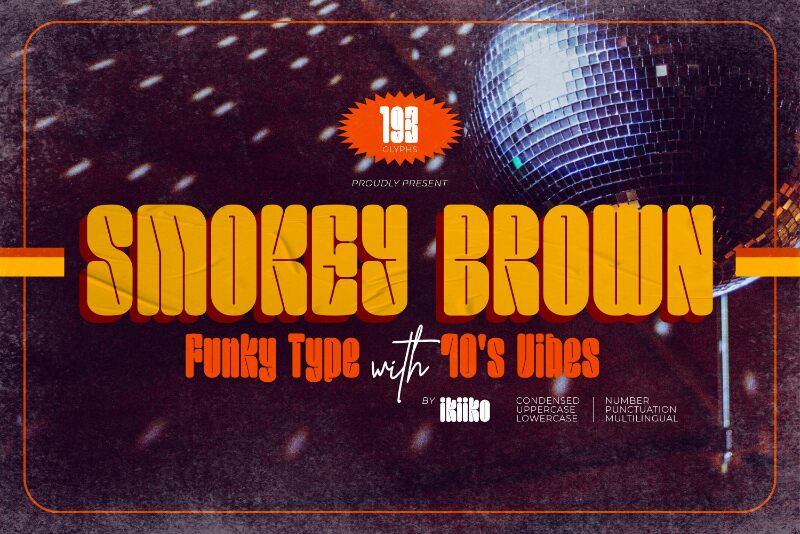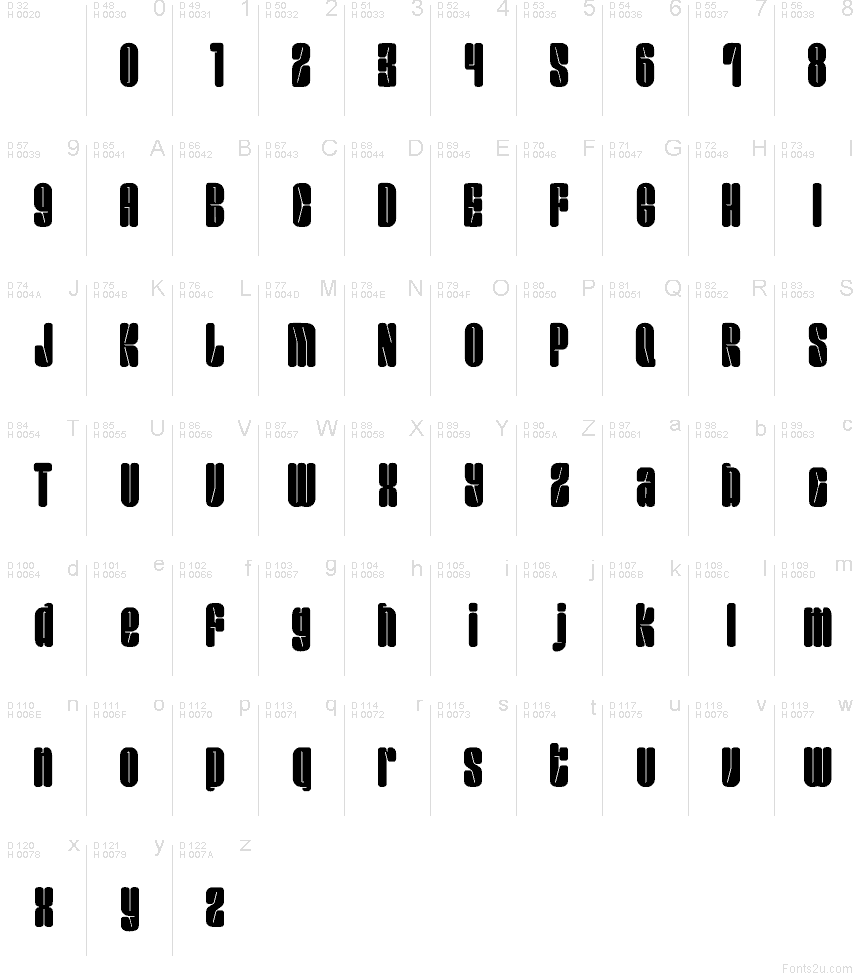
Smokey Brown od Ikiiko Type je bezplatné groovy bezpatkové písmo, které stojí na plných, vzpřímených tvarech. Působí hutně a kompaktně, s typickými úzkými drážkami uvnitř písmen. Tato silueta dodává písmu výrazný vzhled plakátů ze 70. let, kde zaoblené hrany udržují měkkost, i když je celková černá hmota dominantní.
Skvěle se hodí pro přebaly alb, branding kaváren, letáky na akce, obaly nebo grafiku na sociální sítě, kde potřebujete, aby krátká slova fungovala jako silné grafické prvky. Díky husté struktuře a prořezům mají nadpisy pomalý, vláčný rytmus, který se k nostalgickým tématům hodí mnohem lépe než neutrální styly.